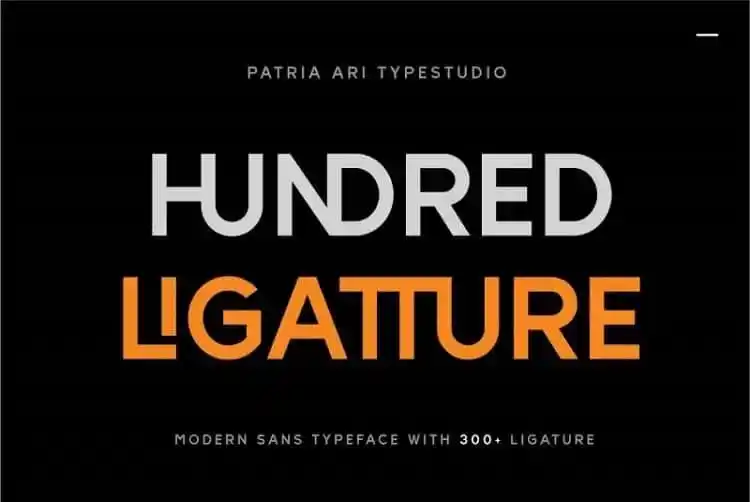
Hundred Ligatture Sans Serif Font – Fonte Grátis
Hundred Ligatture Sans Serif Font
A Fonte ‘Hundred Ligatture Sans Serif’ é uma escolha ideal para quem busca um tipo bold e moderno, com mais de 300 ligaturas dispendiosas prontas para combinação. Desenhada pelo Patria Ari Typestudio, esta fonte sans serif traz a modernidade necessária para estilos de design variados – desde o design editorial até as peças de marca e embalagens. Ela é perfeitamente adaptável às grandes e pequenas headlines, ideal tanto para uso em site quanto nos veículos de mídia tradicionais como rádio e televisão. Uma das principais características desta fonte é seu amplo conjunto de ligaturas dispendiosas, que permitem um grande nível de personalização para seus projetos. Com uma variedade tão extensa, a ‘Hundred Ligatture Sans Serif’ pode ser usada de maneiras inimagináveis, seja em designs visuais altamente detalhados ou em propostas simplistas. Sua simplicidade e modernidade fazem dela um ótimo aliado para quem busca uma tipografia elegante e sofisticada que se adapta a várias aplicações profissionais.